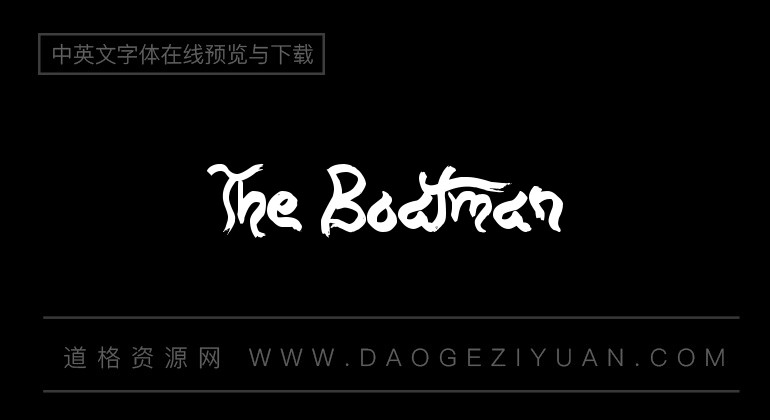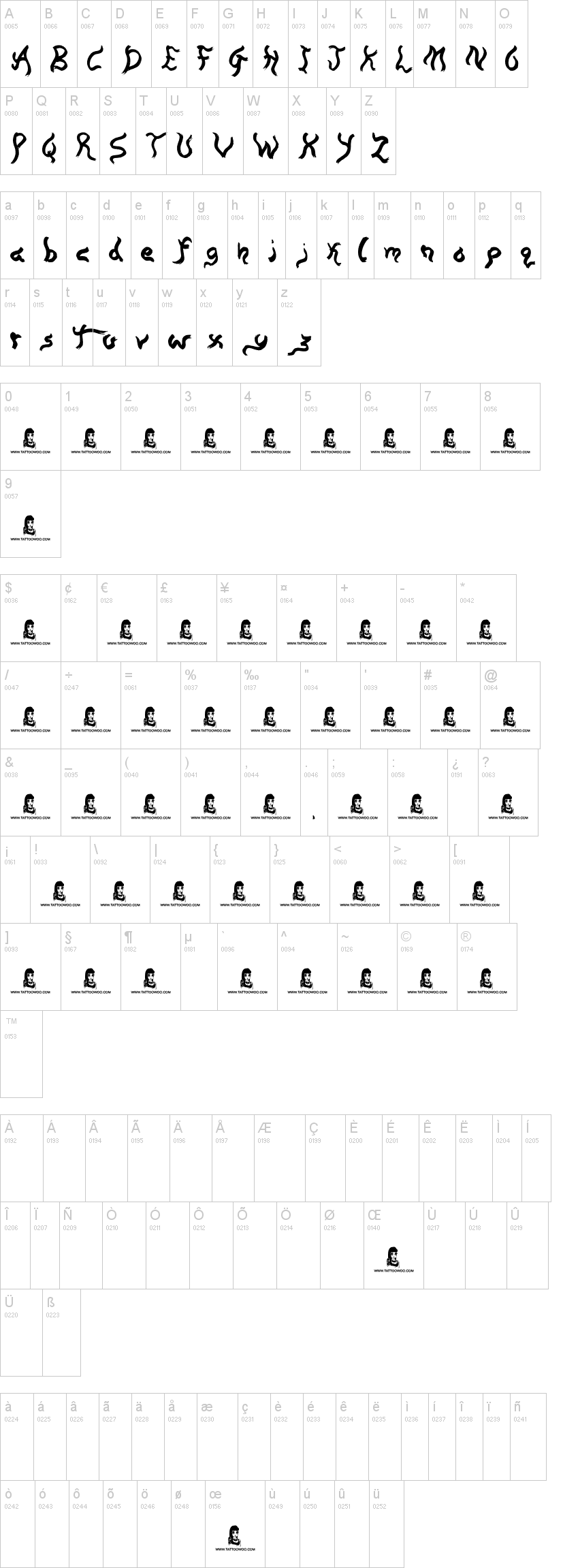
The Boatman
The Boatman 是一款英文字体,由英国设计师Adam Ladd设计。它是一款粗体、抽象的字体,具有较强的表现力,可以把普通的文本转变为有趣的文字。这款字体可以用于标题、标签、海报等等,有助于制作出独特的视觉效果。它的特点是简单、粗犷,可以很好地表达出设计师的创意。
The Boatman是一款非常不错的手写艺术字体,具有很好的视觉感,适合于文化类的宣传设计、商业类品牌的广告和产品包装设计以及个性化文字排版等较多场景。